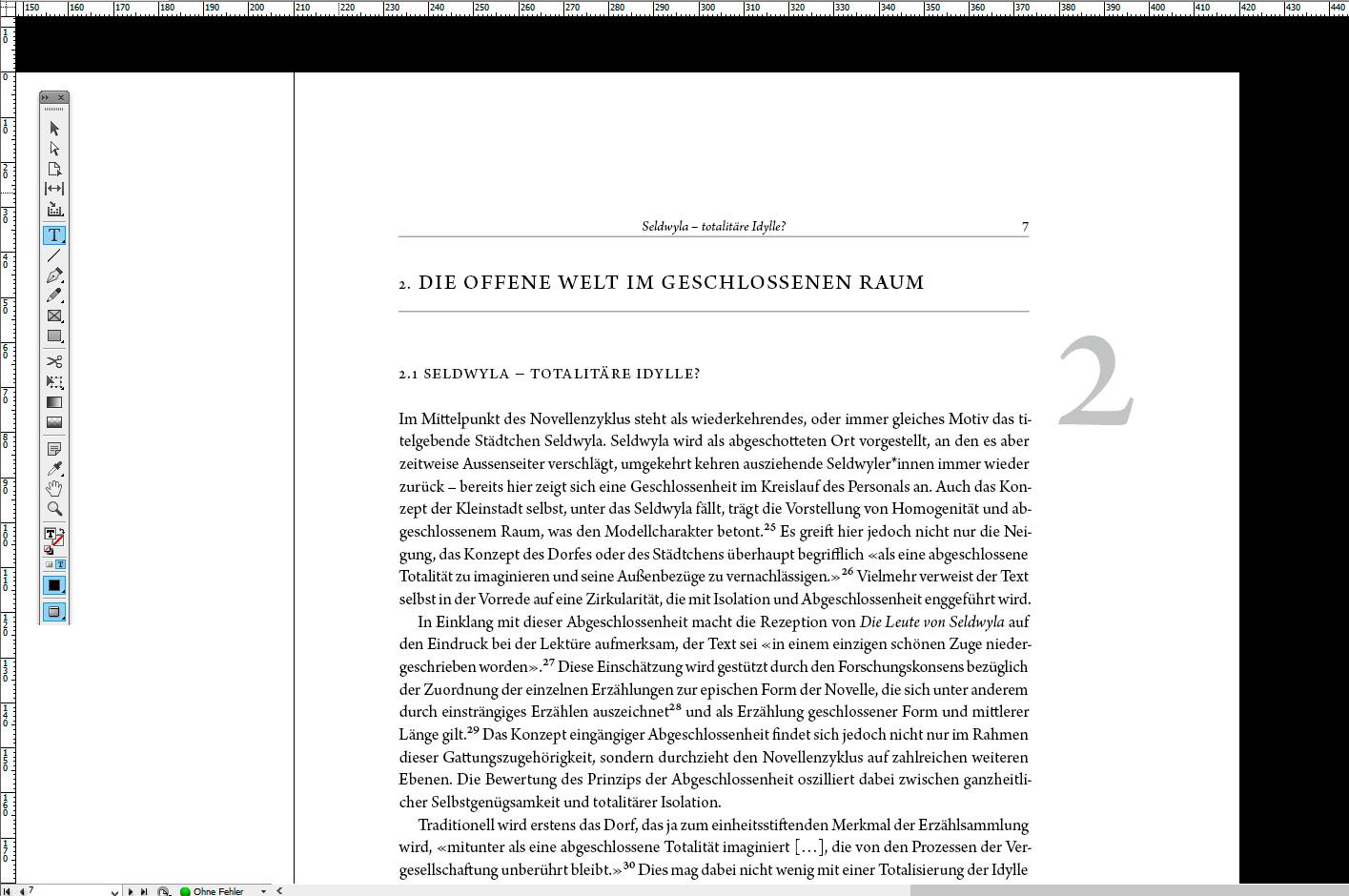
Kapitelnummer in gross ausserhalb des Satzspiegels?
Meine Frage bezieht sich auf die Kapitelüberschrift erster Stufe, da die Kapitelnummer in gross ausserhalb des Satzspiegels steht.
Gerne wollte ich mich erkundigen, was ihr davon haltet. Ist das typographisch so vertretbar? Wie sieht es aus wen die «2» vor dem ausgeschriebenen Titel ganz wegfällt und nur die graue Ziffer steht?
Es handelt sich dabei um ein 70-Seitiges Dokument mit 5 Hauptkapiteln erster Stufe. Nur die Hauptkapitel fallen aus dem Rahmen.
Warum steht denn die graue 2 auf Höhe der Unter-Überschrift "2.1" ?
Der Kolumnentitel sollte auf dieser Seite auch noch entfallen.
P.S. Der Text könnte noch ein Lektorat vertragen, auch Orthographie und Zeichensetzung würden sich über eine Überprüfung freuen.
Die graue 2 steht nicht aus einem bestimmten Grund genau auf der Höhe der Unter-Überschrift. Beides ist einfach am Zeilenregister ausgerichtet und beispielhaft folgt auf dieser Seite der Überschrift eine Unterschrift. Manchmal folgt auch kein Unterkapitel.
Zur Zeit ist der Text noch im Lektorat. Die Zeichensetzung bezieht sich entsprechend auf Kommas, nehme ich an, einmal abgesehen vom Asterisk?
Warum steht die zwei an so prominenter Stelle? Muss diese beim Druchblättern besonders ins Auge fallen? Wenn du den Inhalt der Kapitelüberschirft hervorheben wolltest, damit der Leser dort einsteigen kann, könnte ich das verstehen, aber für eine Zahl sehe ich keinen Grund, außer den der Dekoration. Und für Deko gibt es keine Regeln, die macht man oder macht sie nicht. Meiner Ansicht passt die Zahlendeko nicht zum Inhalt.
Ich würde auch meinen, man kann Dekoration vertreten, wenn man sie vertreten möchte. Sie sollte dann aber vertretbar gesetzt sein. Wozu die große 2 nötig ist, bleibt mir verborgen. Schmuck ist nicht nur unnötiges Beiwerk, im besten Falle wirkt er als Teil eines Gedankens, eines Entwurfs und würde eine Lücke reißen, wenn man ihn wegnähme. Diese 2 ist dagegen entbehrlich.
Die Raumverteilung dieses Kapitelkopfes ist allerdings ziemlich wirr. Dadurch wirkt die große 2 wie eine Ablenkung von den nicht gut angeordneten Räumen: erste Zeile klebt an Linie, danach folgen Zeilen und Linien mit insgesamt vier horizontalen Räumen, die sich nicht aufeinander beziehen, jeder hat seine eigene Größe, alles steht nur irgendwo willkürlich herum. Die große 2 hängt zu tief. Solche Elemente werden nach rein optischen Überlegungen eingesetzt, Bezüge wie Register sind hier nicht immer sinnvoll, weil die 2 in ihrer Gesamtform aus dieser Einteilung fällt.